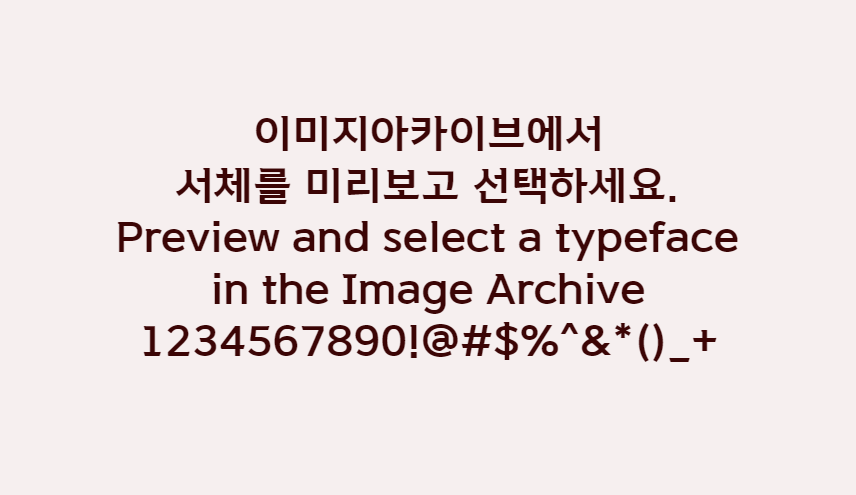
김해가야체
김해가야체 Bold는 가야의 기마병을 모티브로 한 서체입니다. 강인하고 용맹한 인상을 보여주기 위해 단단하고 안정적인 평체 구조로 디자인되었습니다. 'ㅎ'의 꼭지는 투구의 모습을 담았고, 'ㄱ,ㄷ'등의 자소에서 철갑옷의 단단함을 표현하였습니다. 전체적으로 가로줄기의 돌기와 맺음에 사선값을 줌으로써, 힘차게 달리는 가야 기마병의 역동성을 담은 서체입니다.
김해가야체 Regular는 Bold에서 느껴지는 이미지를 그대로 적용해 단단하고 안정적인 평체 구조를 가지고 있습니다.
Regular 굵기의 용도에 적합하도록 돌기를 완화하고 곡선을 부드럽게 하는 등 외형적인 특징을 절제하여 작은 크기에서의 가독성에 초점을 맞추어 디자인 되었습니다. 자소의 특징으로는 'ㄱ,ㅎ'과 같이 형태적 모습과 세로줄기의 돌기 같은 특징적인 형태를 Bold 굵기의 자소와 같은 인상으로 디자인하여 서체 패밀리의 통일성을 높였습니다.
깔끔한 고딕류의 폰트로 획의 꺽임이 세련되게 디자인되어있는 모습으로 역동성을 표현했다고하는데 그말이 어느정도는 이해가 가는 모습입니다. 폰트는 2개의 구성으로 Bold, Regular체를 배포중입니다. 한글 11,172자, 영문94자로 구성되어 있습니다.